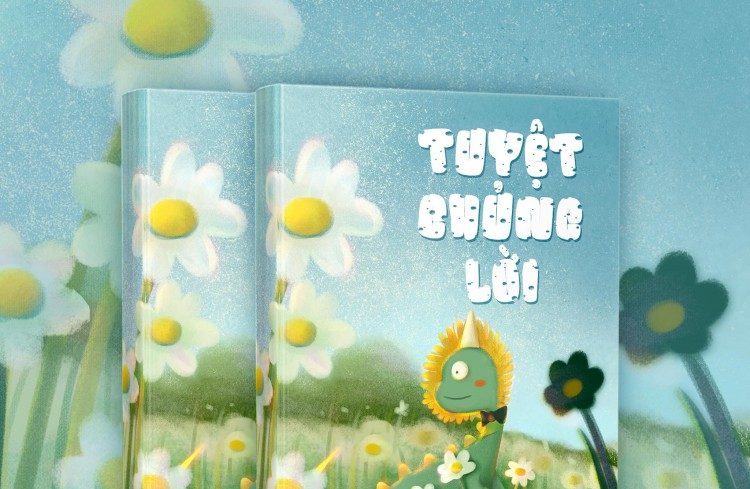
Font việt hoá TP Happy Dinosaur
Trong thế giới thiết kế dành cho trẻ em, việc lựa chọn một bộ Font Miễn Phí phù hợp đóng vai trò cực kỳ quan trọng để thu hút sự chú ý của các bạn nhỏ. Font việt hoá TP Happy Dinosaur chính là lựa chọn hoàn hảo mang đến sự ngộ nghĩnh và năng động cho mọi dự án giáo dục. Với các đường nét bo tròn mềm mại mô phỏng hình ảnh những chú khủng long đáng yêu, bộ font này giúp các bài giảng và tài liệu học tập trở nên sinh động hơn bao giờ hết.
Ưu điểm nổi bật của Font việt hoá TP Happy Dinosaur
Thiết kế thân thiện và gần gũi
Đặc điểm lớn nhất của Font việt hoá TP Happy Dinosaur là phong cách vui nhộn, mang đậm chất hoạt hình. Các ký tự được thiết kế không góc cạnh, tạo cảm giác an toàn và dễ chịu cho mắt trẻ nhỏ. Điều này rất có lợi trong việc kích thích tư duy sáng tạo và lòng yêu thích học tập của học sinh tiểu học và mầm non.
Hỗ trợ tiếng Việt hoàn chỉnh
Khác với các bộ font gốc thường gặp lỗi dấu khi đánh tiếng Việt, phiên bản này đã được tinh chỉnh kỹ lưỡng. Các dấu thanh được đặt vị trí chuẩn xác, giúp văn bản trình bày chuyên nghiệp và mạch lạc. Bạn có thể sử dụng bộ font này trên nhiều phần mềm thiết kế như Canva, Photoshop hay Word một cách dễ dàng.
Ứng dụng thực tế trong giáo dục và thiết kế
Các thầy cô giáo có thể sử dụng bộ font này để làm tiêu đề bài giảng PowerPoint, thiết kế phiếu bài tập hoặc trang trí không gian lớp học. Ngoài ra, các phụ huynh cũng thường dùng để làm thiệp mời sinh nhật hoặc dán nhãn vở cho con. Font việt hoá TP Happy Dinosaur không chỉ đẹp mà còn truyền tải năng lượng tích cực đến người xem.